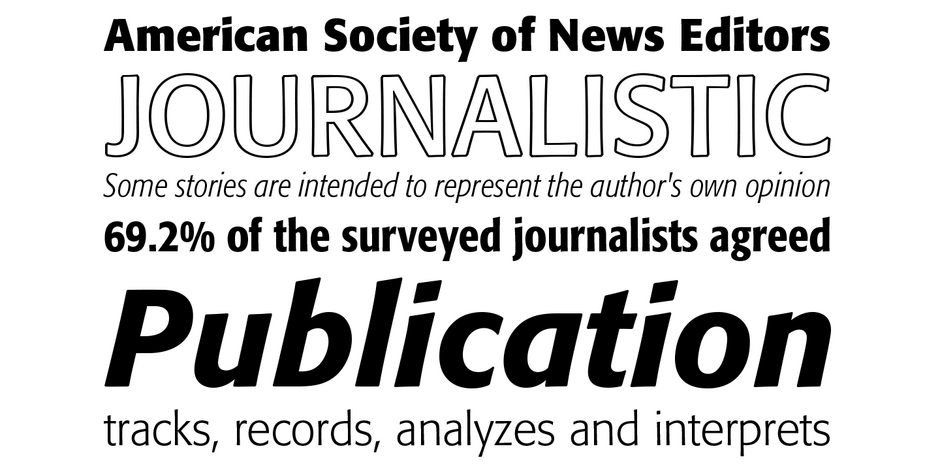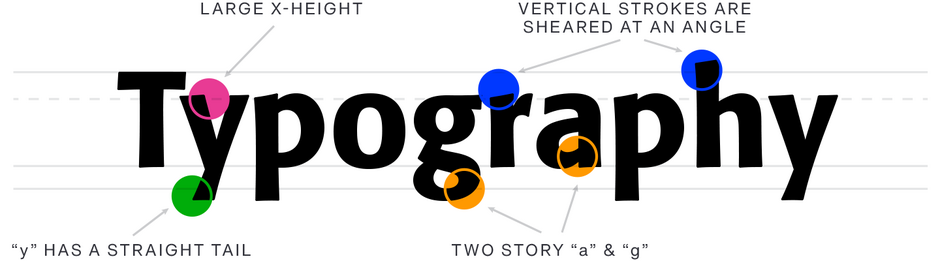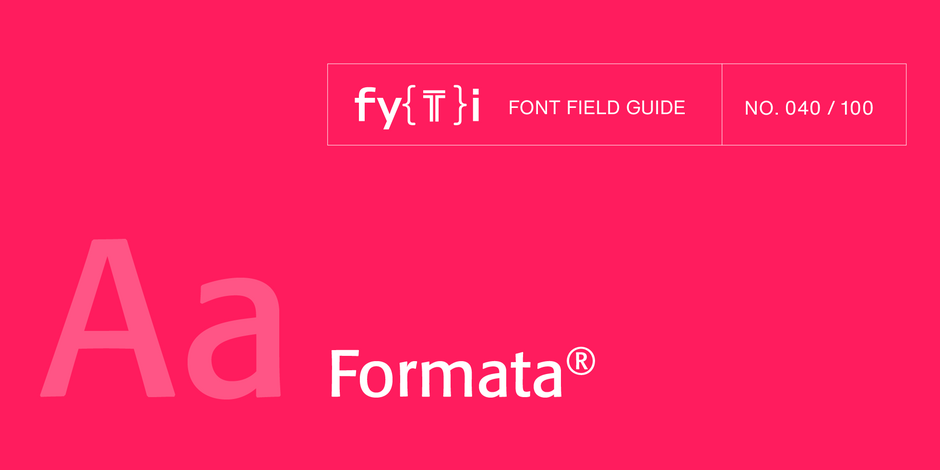
Guide d'utilisation des polices de caractères Formata
FONDERIE :Berthold
CONCEPTEUR :Bernd Möllenstädt
CLASSIFICATION :Humanistic Sans
Meilleures pratiques
L'étendue de la famille Formata en fait un excellent choix pour un large éventail d'applications, depuis les blocs de texte jusqu'aux titres des panneaux d'affichage. Ses caractéristiques subtiles ne sont pas immédiatement apparentes dans les petites tailles, mais elles ajoutent une touche distinctive à mesure que la taille du point augmente.
Famille
La famille Formata compte 26 styles : quatre graisses de caractères réguliers, quatre graisses de caractères condensés et quatre graisses de caractères extra condensés - tous avec des italiques complémentaires - plus deux caractères de contour.
Faits concernant les polices de caractères
- Formata, est sorti en 1984. La famille s'est enrichie de styles condensés en 1988 et de styles extra condensés en 2007.
- Bernd Möllenstädt, le concepteur de Formata, était à la tête du département de création de caractères chez Berthold.
Racines
Formata puise ses racines dans les formes calligraphiques. Ses courbes subtiles et ses formes fluides allient les nuances calligraphiques traditionnelles à une éthique moderne. Le résultat est un design qui fait le lien entre la formalité et l'accessibilité.
Lisibilité
Les racines calligraphiques de la Formata et ses minuscules pleines créent un flux horizontal naturel pour les mots et les blocs de texte. Cette caractéristique, combinée à ses minuscules a et g à deux étages, à ses ouvertures ouvertes et à ses généreux guichets, favorise la lisibilité sur papier et à l'écran.
Comment repérer les Formata